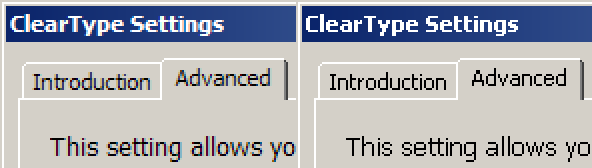
Fragen zum Schriftkauf (Multiuser-Lizenz, Hinting, MSOffice)
ich möchte für die Firma, in der ich arbeite eine Schrift kaufen und hab dazu einige Fragezeichen im Kopf, von denen ich hoffe, dass ihr sie beseitigen könnt! :P
anfragen möchte ich die Kosten für die Meta, Officina und Unit FF.
Folgende Bedingungen habe ich an die Schrift:
benötigt werden die 4 "typschen" Schnitte roman, kursiv, fett, fett/kursiv
verwendet werden sie hauptsächlich in MS Office Programmen (Word, Excel) am PC
Tabellenziffern soll die Schrift haben
Eurozeichen wird auch unbedingt benötigt
jetzt bietet Fontshop natürlich alles mögliche an und ich würde von einen Dingen gerne wissen, wie weit die Sachen wirklich was bringen:
Das Beispiel auf der Fontshop Website über zeugt mich nicht wirklich, dass die Schrift dann bei Office-Anwendungen dadurch soviel besser lesbar wird, wie zB die Arial oder Verdana.
Hat da jemand Erfahrungen, wenn Schriften von Fontshop für den Bildschirm optimiert werden? Zahlt sich die Investition aus? Fontshop emphielt dann TrueType-Schriften - passt das?
3. Stilverlinkung: Fontshop bietet an, dass die Schriftschnitte über den Stilbefehl erreichbarsind - fehlerhafte elektronische Fett- und Kursivstellungen in Office-Programmen sollen dadurch ausgeschlossen werden. Das ganze kostet 235 €. Macht sich das bezahlt? Oder ist das eine einfache Einstellung in den Office-Programmen, die man selbst vornehmen kann? Bzw. sollte das nicht automatisch funktionieren? Die künstliche Fett- oder Kursivstellung will ich natürlich nicht haben. Wovon hängt das überhaupt ab?
4. Tabellenziffern: ist es gut, die von Fontshop erstellen zu lassen, wenn der Font keine Tabellenziffern enthält?
Die kurze Antwort: Alle deine Fragen kreisen um das Thema »Office-Anwendung«. Und genau für diesen Zweck gibt es auch fertige Pakete – das muss man sich nicht alles extra erstellen lassen. Halte einfach nach der Bezeichnung »Office« im Schriftnamen Ausschau. FF Fago Office, FF Info Office, PTL Manual Office und so weiter.
Aber die wollen natürlich ihre Podukte verkaufen. Daher will ich ja wissen, wer mit den Servicegeschichten schon Erfahrung hat und mir sagen kann, ob sich die einzelnen Pakete zur Optimierung (Hinting, Stilverlinkung,...) überhaupt bezahlt machen oder ob es eher eine Bauernfängerei ist und Einstellungen auch zb im Word getroffen werden können.
"Office" hab ich leider nirgends im Schriftennamen entdecken können
von der Officina allerdings die Windows True Type-Version.
Bedingt die, dass sie für MS Office optimiert wurde?
und dann noch die FF Meta Correspondence
da ist mir auch nicht klar, ob das die richtige sein könnte.
bei der Unit hab ich gar nichts treffendes finden können.
oder bin ich einfach blind und suche falsch?
es gibt eine meta office (aus der europaschriften reihe)
Das zeichnet die FontFont-Office-Schriften aus:
- komplette Europa-Sprachausstattung
- 4 Schnitte pro Paket, stilverlinkt
- für Cleartype optimiert
- Tabellenziffern
- TrueType-Outlines
- Lizenz für 5 Arbeitsplätze enthalten
- attraktive Mengenrabatte für Multilizenzen
die funktionieren gut auf dem monitor.
Die Europaschriften wurden genau für eure Ansprüche konzipiert und haben zusätzlich noch sehr umfangreiche Sprachausbauten. In dem PDF dort stehen auch Preise, die ungefähr zeigen, was damit auf euch zukommen würde. Auch wenn FontShop natürlich verkaufen möchte, ist die Beratung dort eine der besten, die du kriegen kannst.
Danke. Gut, dass es da die Meta schon mal gibt. Aber was, wenn ich die gleich Anforderungen an die Officina und Unit habe? Man kann sich doch nicht nur auf die wenigen FontFont Europa-Schriften verlassen, die auf der Website jetzt gesehen habe.
@ Jens: Was ist denn in Deinem Bild der Unterschied zwischen der TrueType- und OpenType-Schrift?
Wie gesagt, der Unterschied ist nicht groß. In der größten Größe sieht man ihn schon. Bei TrueType-Schriften kann man z.B. beeinflussen, ab welcher Pixelgröße die Linienstärke von 1 zu 2 Pixel wechselt.
Hier der tatsächliche Vergleich zwischen Unit TT und OT in Word 2007 auf Win XP, einmal mit ClearType und auf dem unteren Bild ohne Glättung.